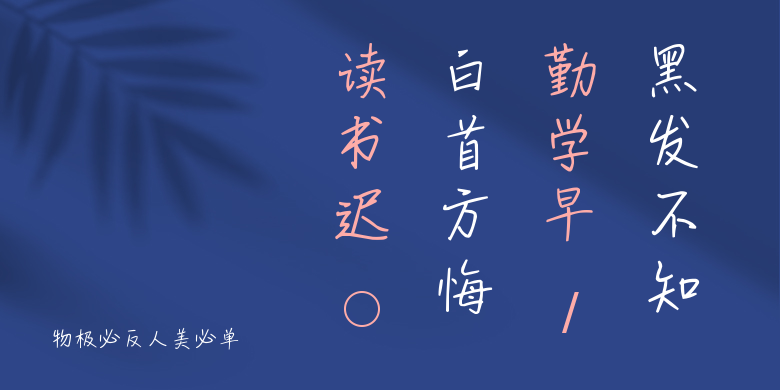
物极必反人美必单
物极必反人美必单,这款字体结构工整、笔画清晰,兼顾美观与易读性,适用于标题、正文、海报、包装、LOGO 等多种场景。字形优雅稳定,风格百搭耐看,适配日常排版与创意设计,让文字呈现更舒适、更具质感。物极必反人美必单一笔一画,皆是细节,以均衡的比例、流畅的线条打造舒适视觉体验,字形端正大气,风格简约现代。无论是商业设计、品牌宣传还是日常排版,都能轻松驾驭,让文字更有格调与力量。物极必反人美必单字体下载。